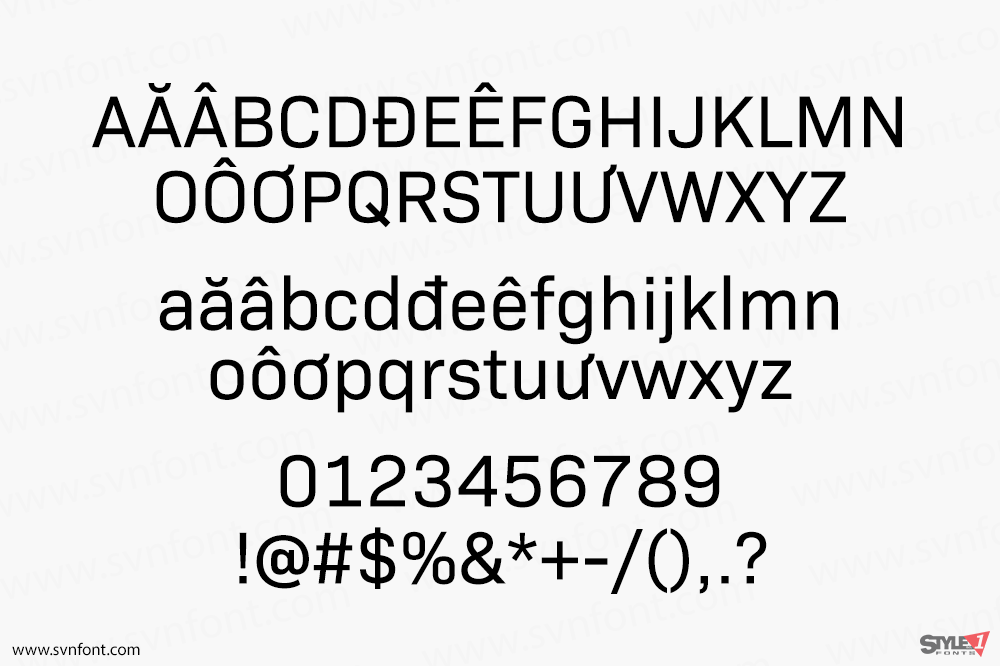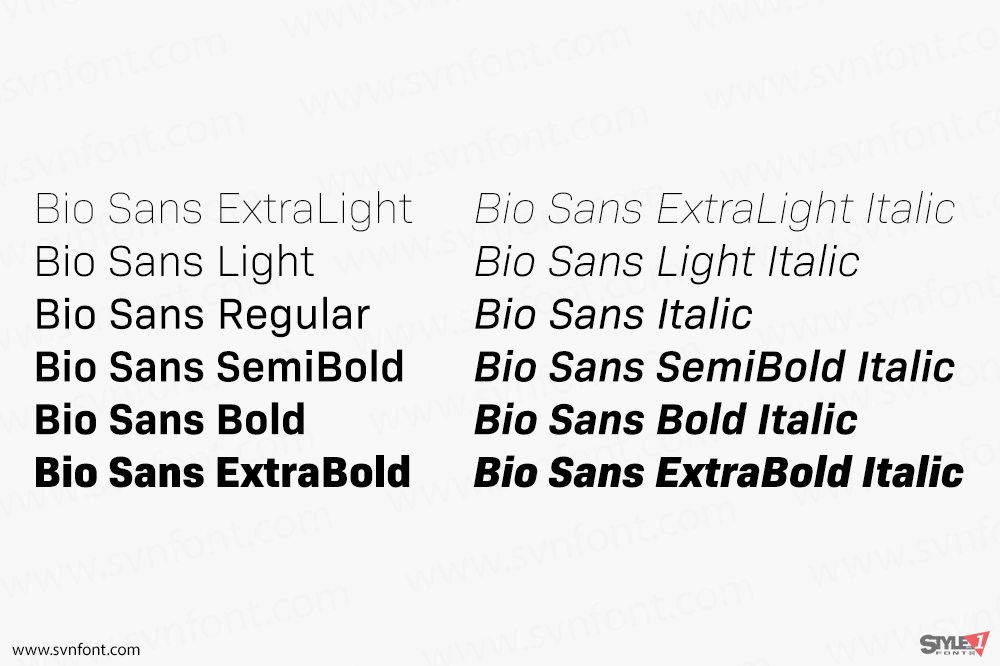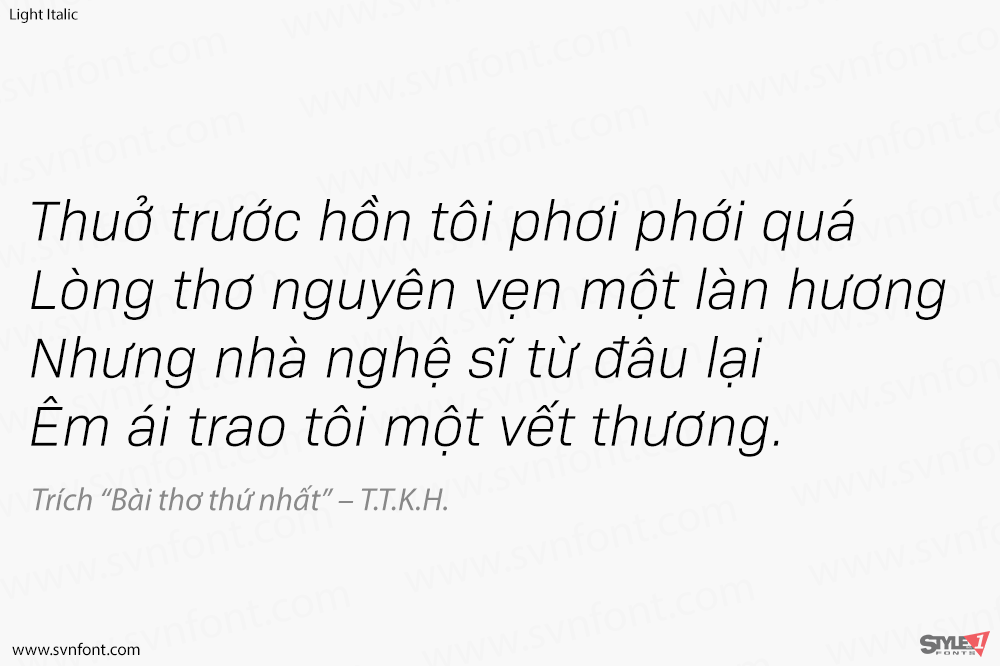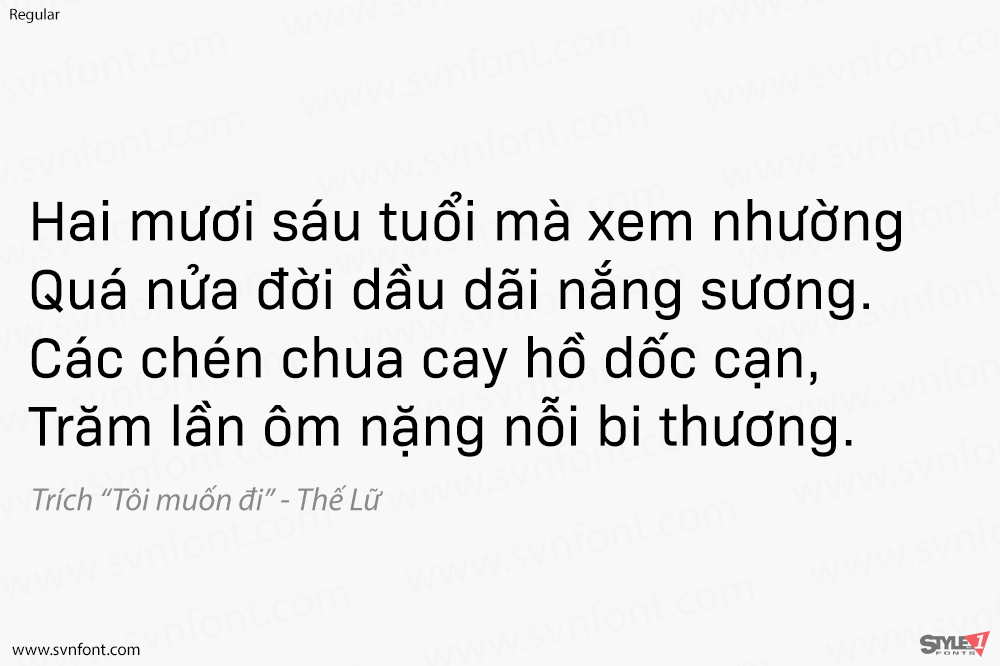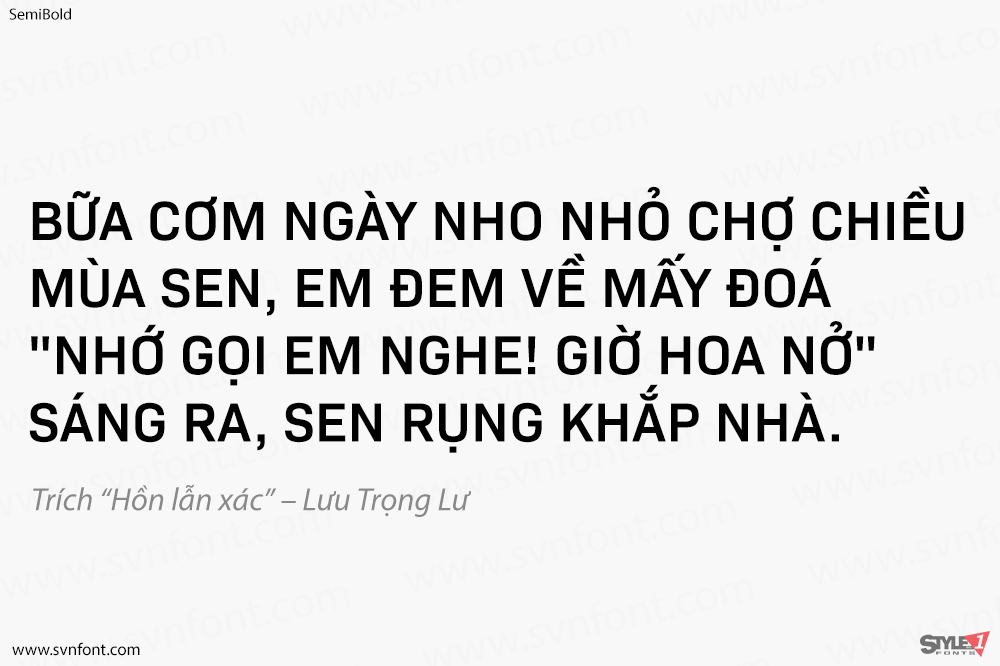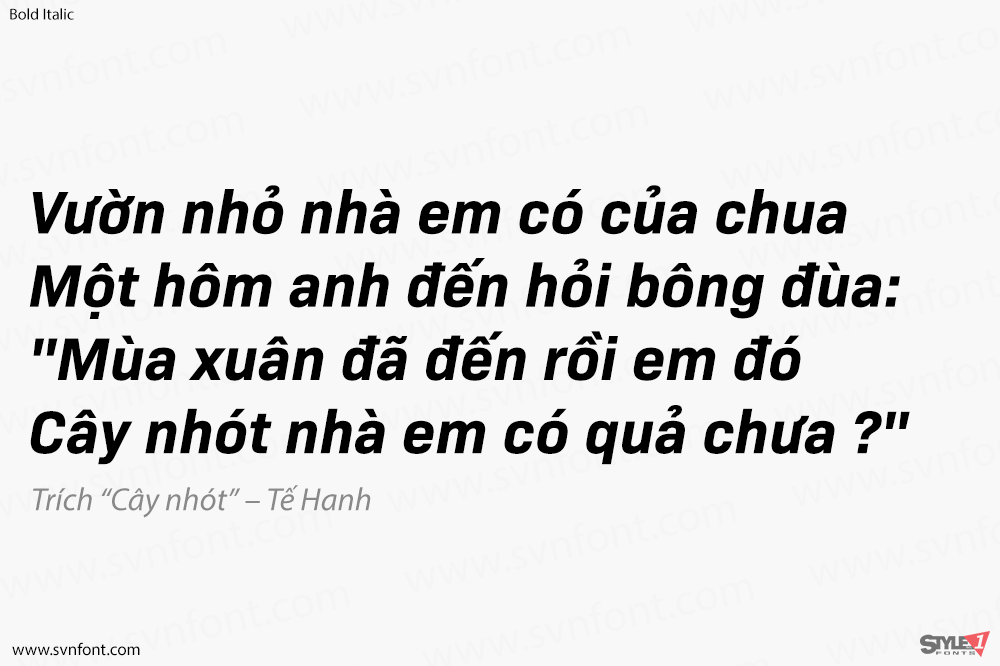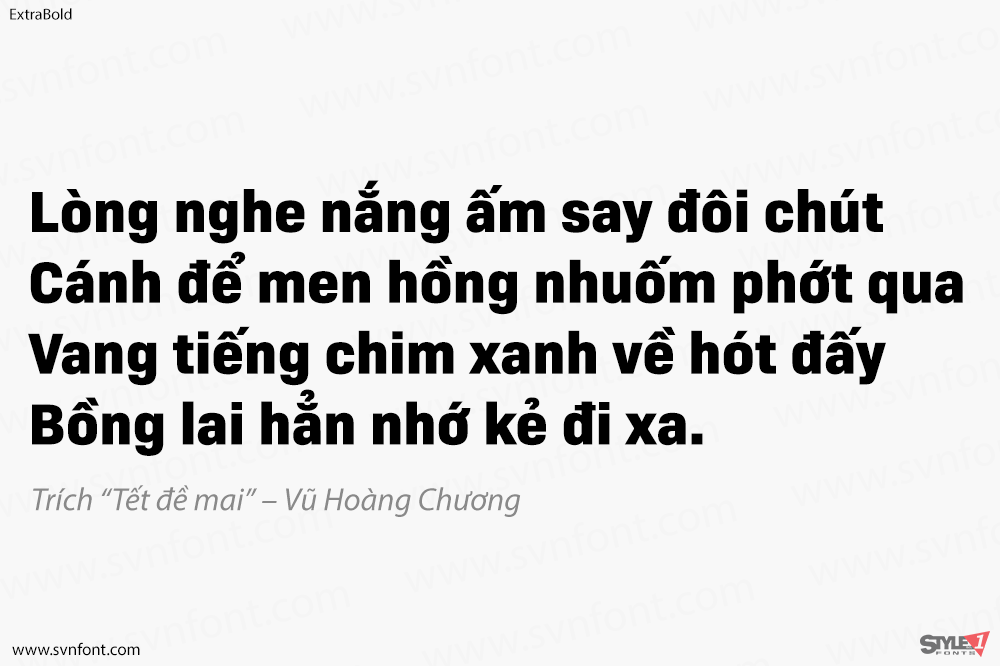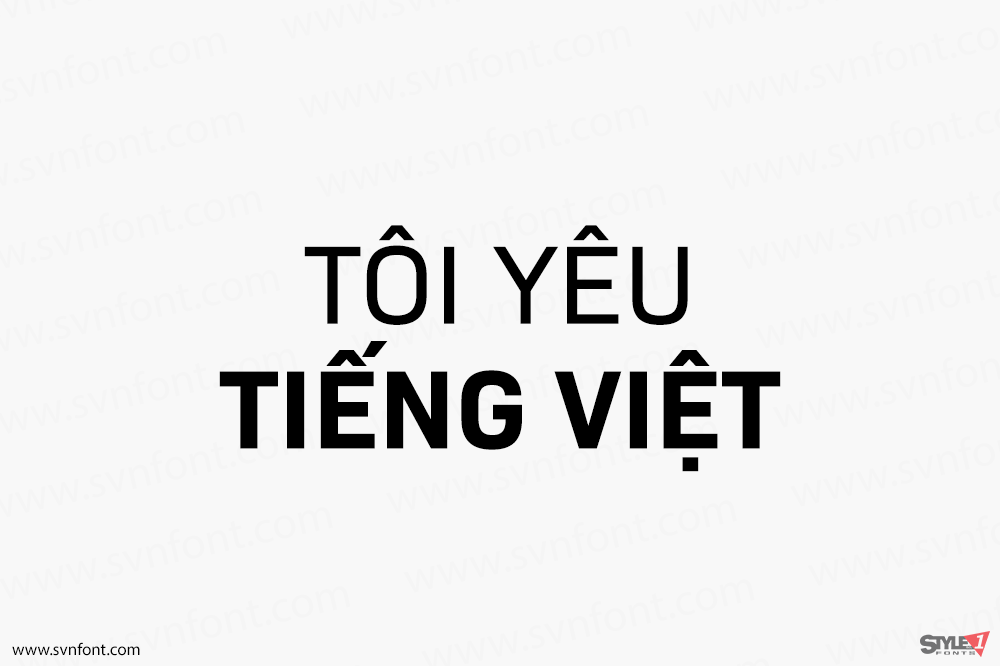
Bio Sans là một họ font sans-serif siêu trung tính dành cho văn bản, được thiết kế bởi Ryoichi Tsunekawa. Toàn bộ họ font này bao gồm 6 độ đậm từ ExtraLight đến ExtraBold và các kiểu chữ Italics tương ứng. Khái niệm cơ bản của họ font này giống như Bebas Neue, font miễn phí phổ biến nhất của chúng tôi và được sử dụng trên toàn thế giới, đó là: Trung tính, Tự nhiên, Tối giản, Vô hại, Siêu phẳng, Trong suốt và Dễ đọc.
Bộ xương cơ bản của hình dạng chữ cái của chúng được thiết kế hình học và thiết kế tinh xảo mang lại cho chúng tính phổ quát, tính trung lập và cảm giác thống nhất để sử dụng trong mọi phương tiện, mọi mục đích. Chiều cao x-height lớn của chúng giúp họ font này dễ đọc ngay cả trên màn hình kích thước nhỏ. Bio Sans hỗ trợ hầu hết các ngôn ngữ châu Âu: Tây, Trung, Đông Nam Âu và tiếng Afrikaans. Các chữ số tỷ lệ (proportional figures), chữ số trên (superior figures), chữ số dưới (inferior figures), mẫu số (denominators), tử số (numerators), phân số (fractions), số thứ tự (ordinals) và các dạng phân biệt chữ hoa chữ thường (case-sensitive-forms) có thể được truy cập bằng cách sử dụng các tính năng OpenType.
Nhà thiết kế: Ryoichi Tsunekawa
Nhà phát hành: Dharma Type